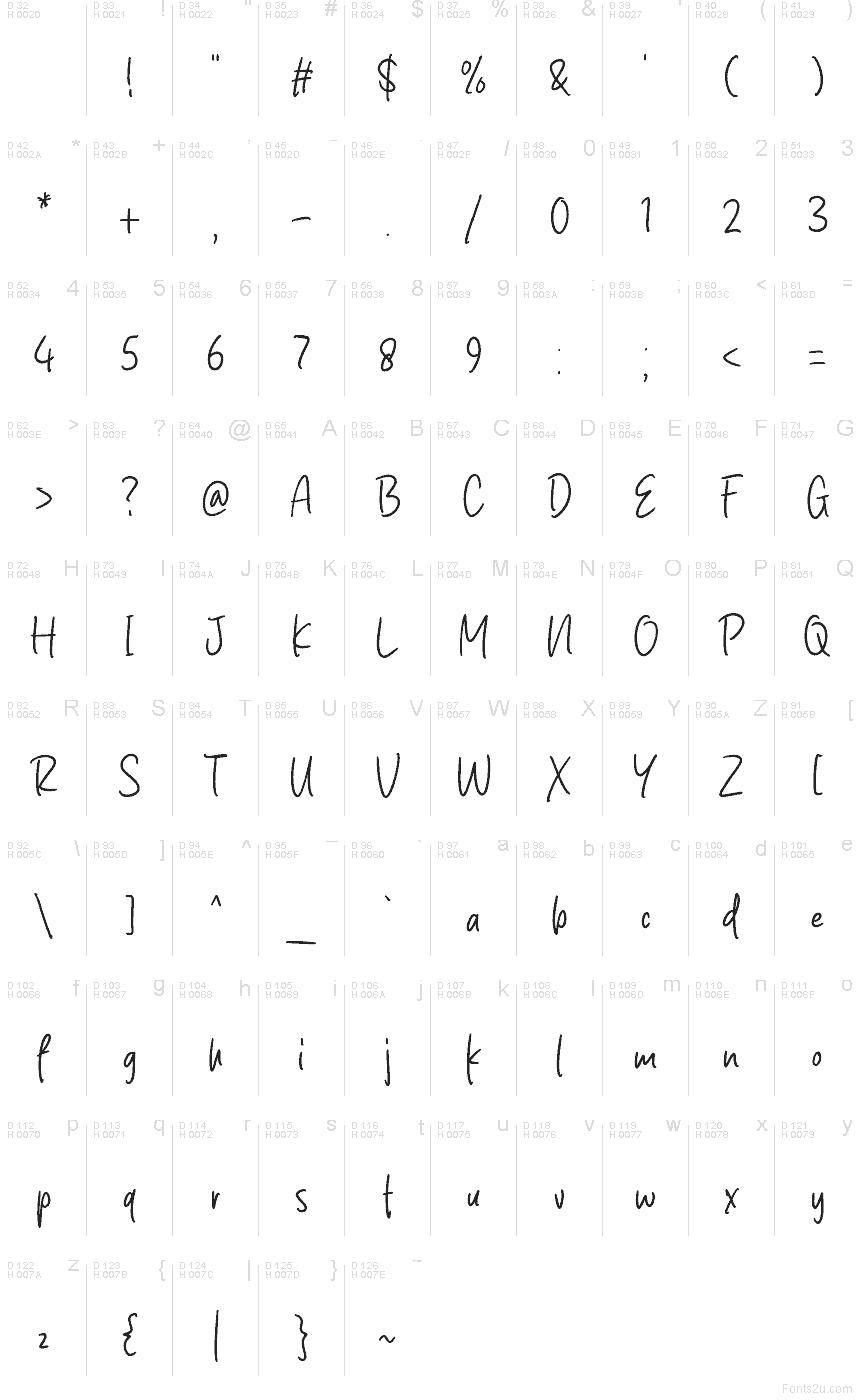
Marline Staylish
Marline Staylish от MJType — это бесплатный рукописный шрифт с настроением небрежной модной подписи. Сочетание высоких, воздушных штрихов и быстрых скругленных соединений придает шрифту непринужденный, но изысканный вид, словно имя написано одним уверенным движением руки.
Он отлично подходит для брендинга бутиков, косметической упаковки, карточек с цитатами для соцсетей, заголовков и меню в кафе, где важен личный акцент, а не строгая формальность. Будучи бесплатным шрифтом, он также хорош для логотипов, приглашений и заголовков, особенно если вы хотите, чтобы его длинный, плавно покачивающийся ритм стал основой стиля.